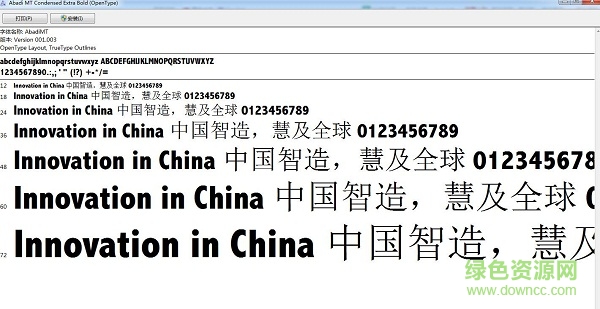
abadimt-condensedextrabold字體是一款柔韌有力的英文粗體字體,風格大方時尚,線條舒展,整體字形力量感十足,可以用作品牌廣告、雜志封面、包裝設計等,喜歡的朋友快來綠色資源網(wǎng)免費下載吧!
英文一般是由數(shù)個字母組合為單詞,再由單詞組成句子和段落, 和漢字一樣,為了確保每個字母在組詞的時候互相不粘連接觸,互相都必須保持相應的空間。這個小小的空間間隔,并不是單一存在的,其實它是由相隔的2個字母互相各空出的 空間組成,這樣,每個字母的兩邊都會保留相應的空間,這個空間及相應的設定行為在字 體設計中被稱為Spacing。